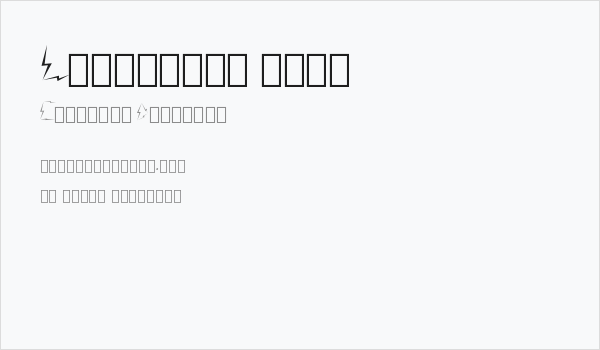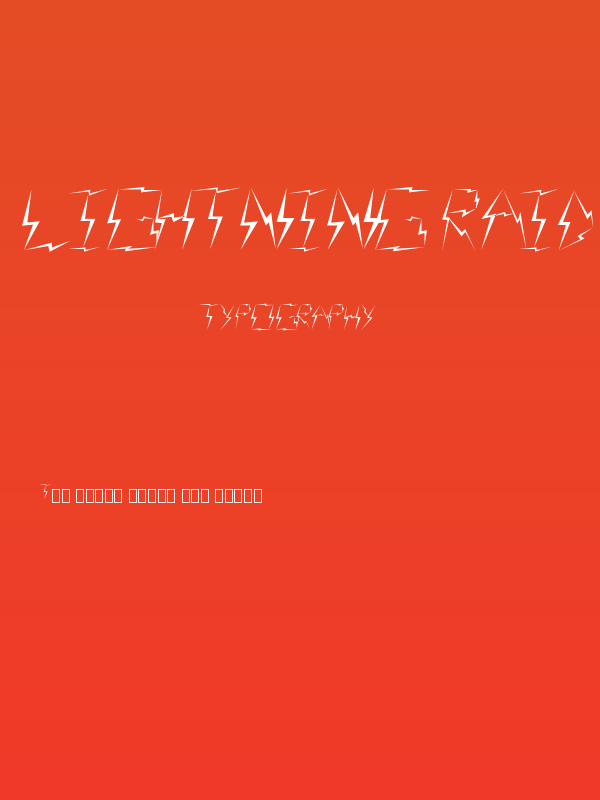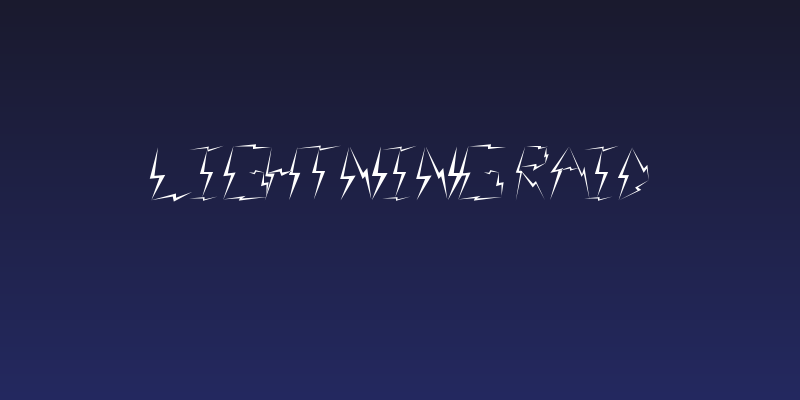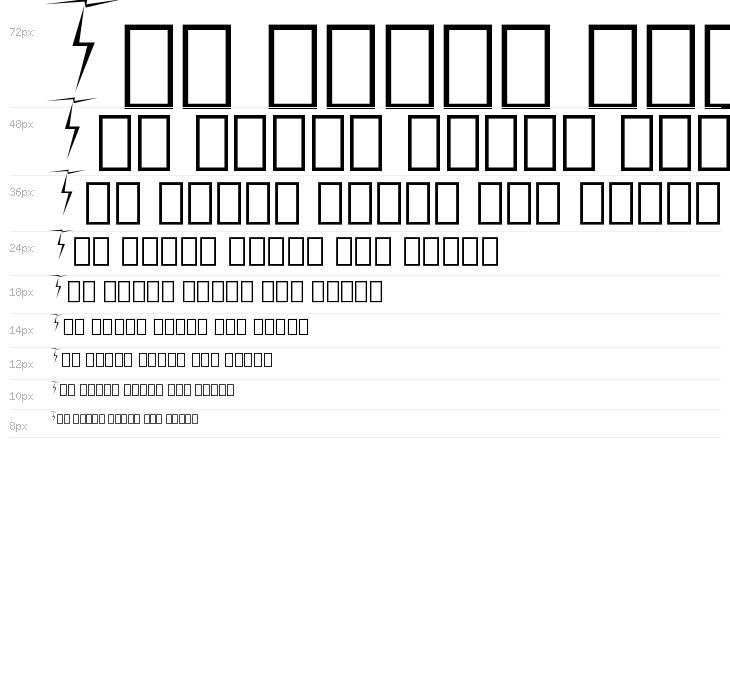
Lightning raid Font
Cette police comprend 31 caractères. Cliquez sur un caractère pour voir les détails.
| Projets proposés | Ideal for music album covers, event posters, and branding for energy drinks or sports teams. |